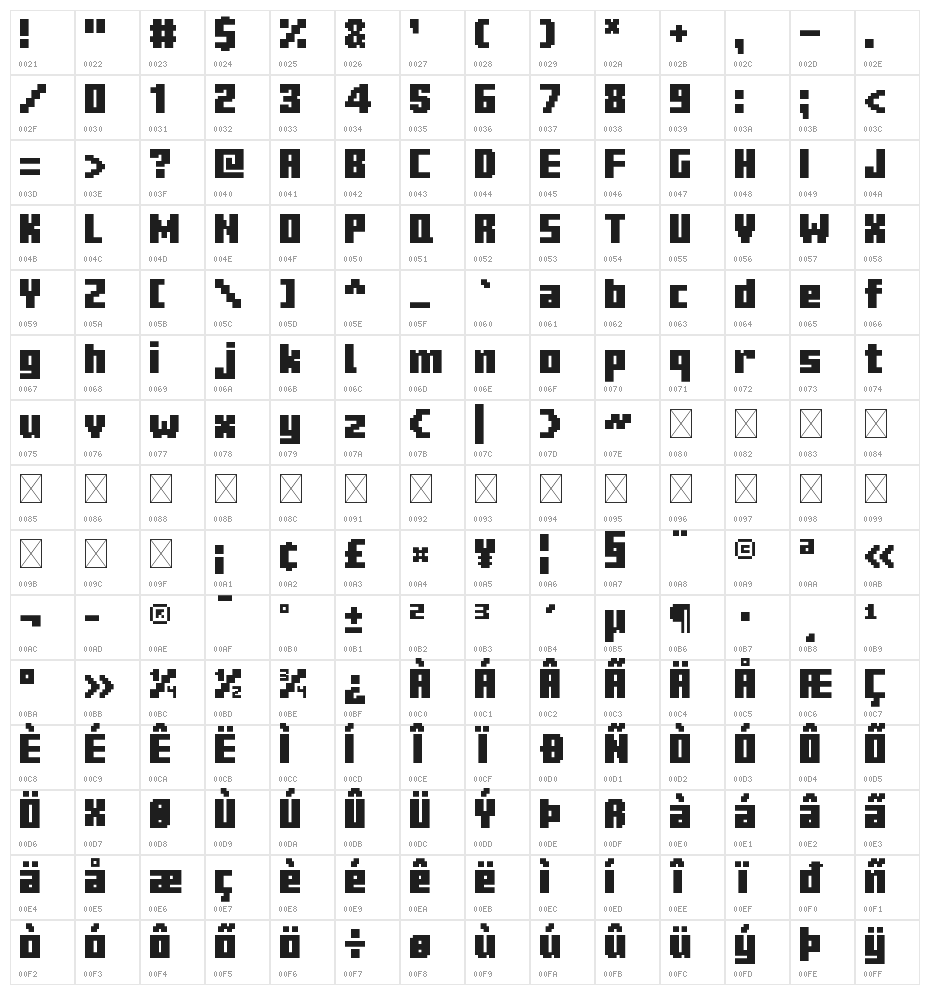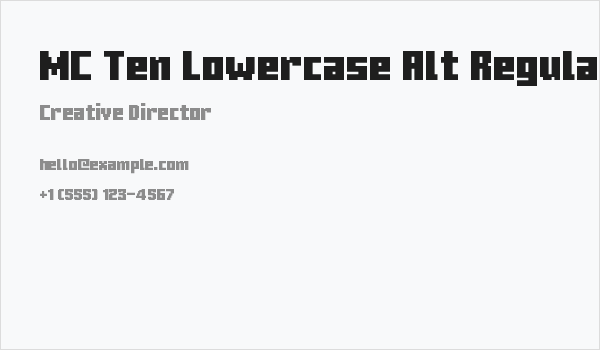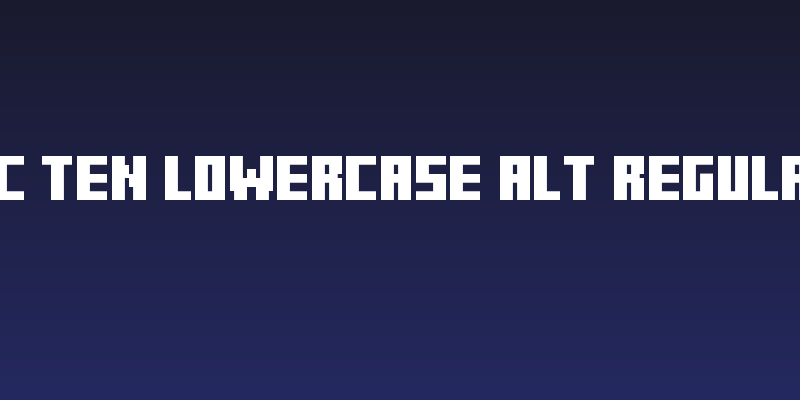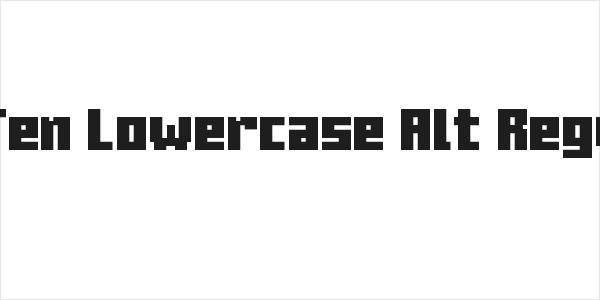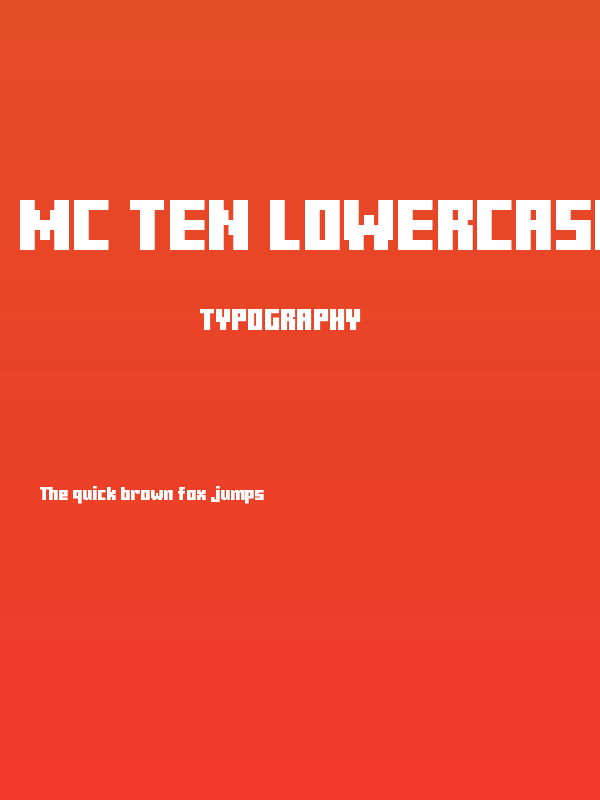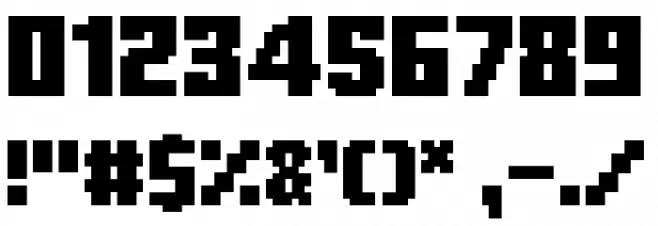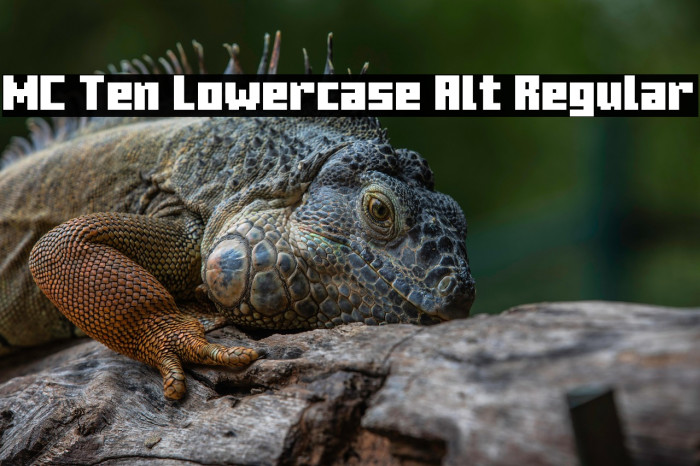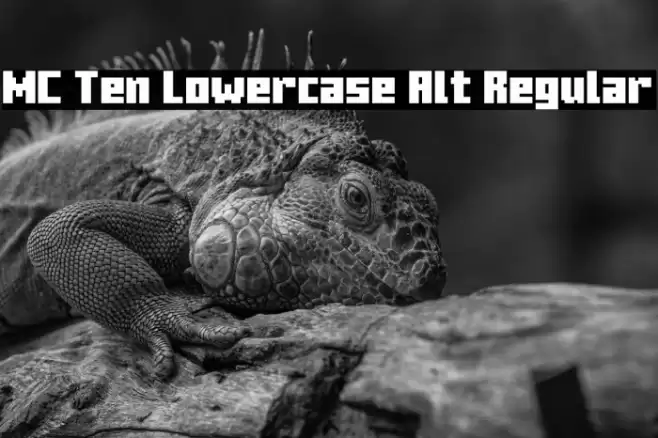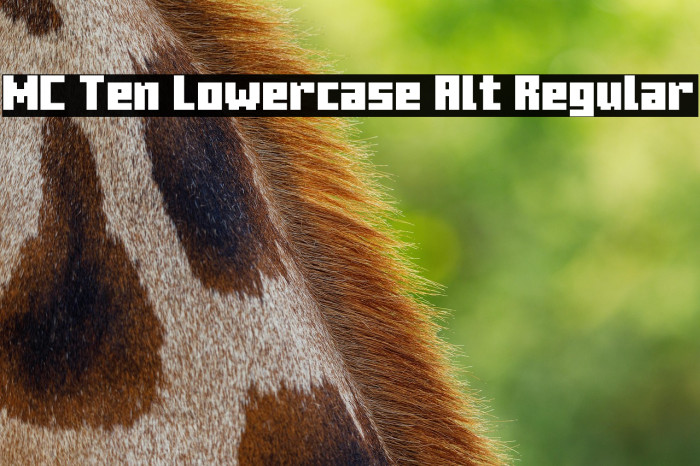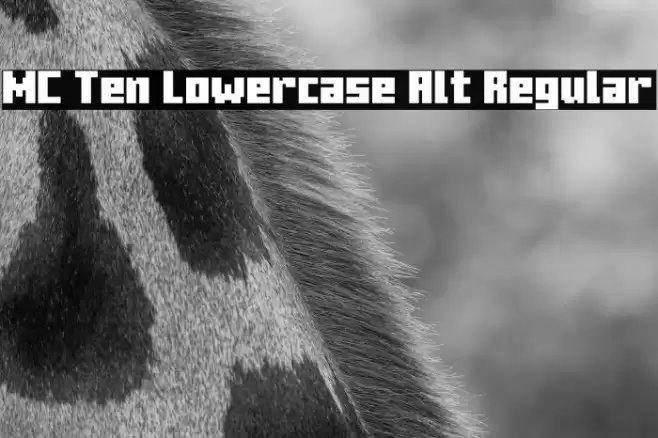
MC Ten Lowercase Alt Regular Font
| الفئات | Pixel |
| النمط العام | Retro, Digital |
| حالة الاستخدام | Logos, Headlines, Posters |
| مشاريع مقترحة | Ideal for video game design, retro-themed posters, digital art projects, and tech-related branding. |